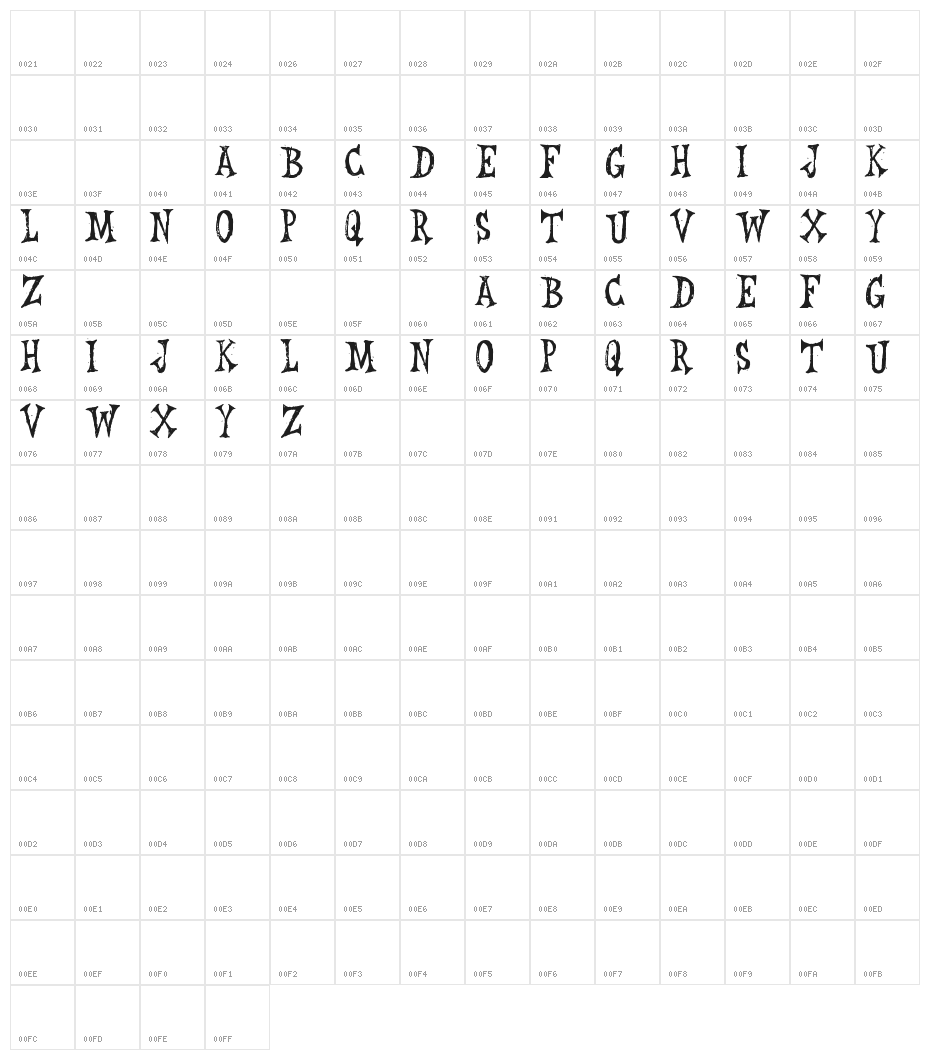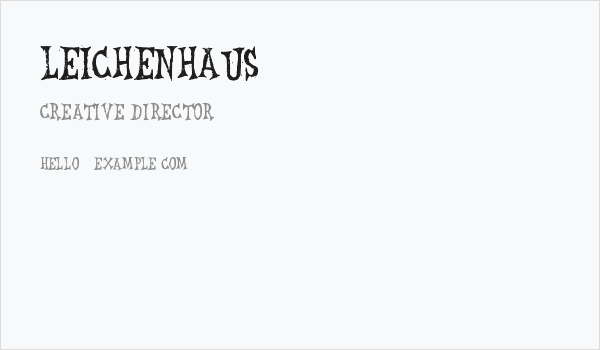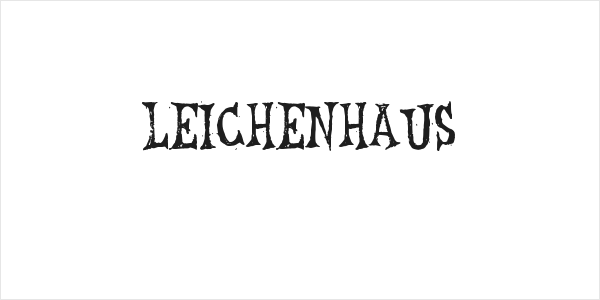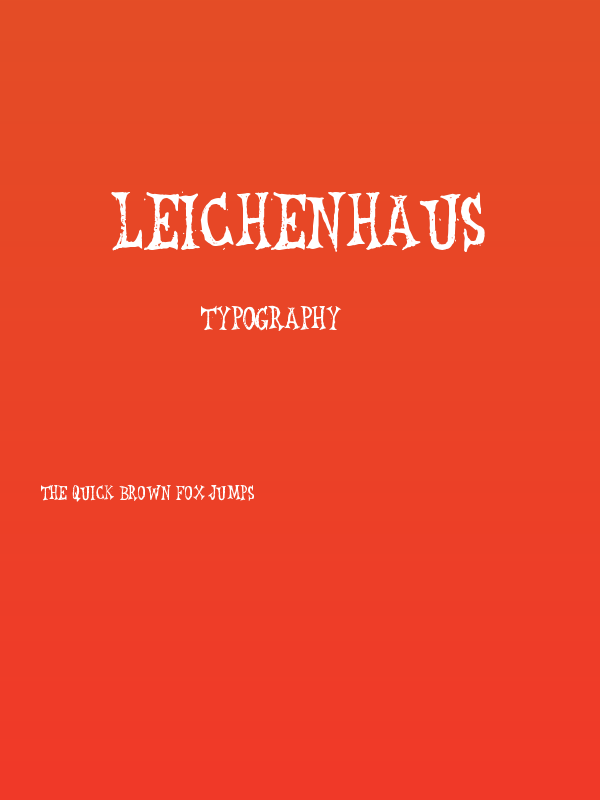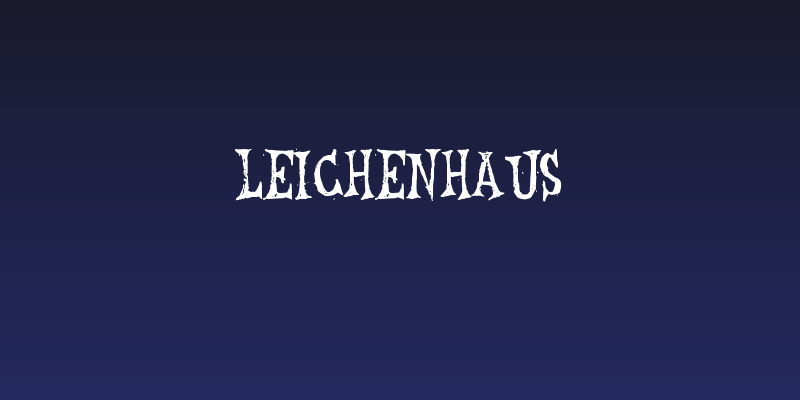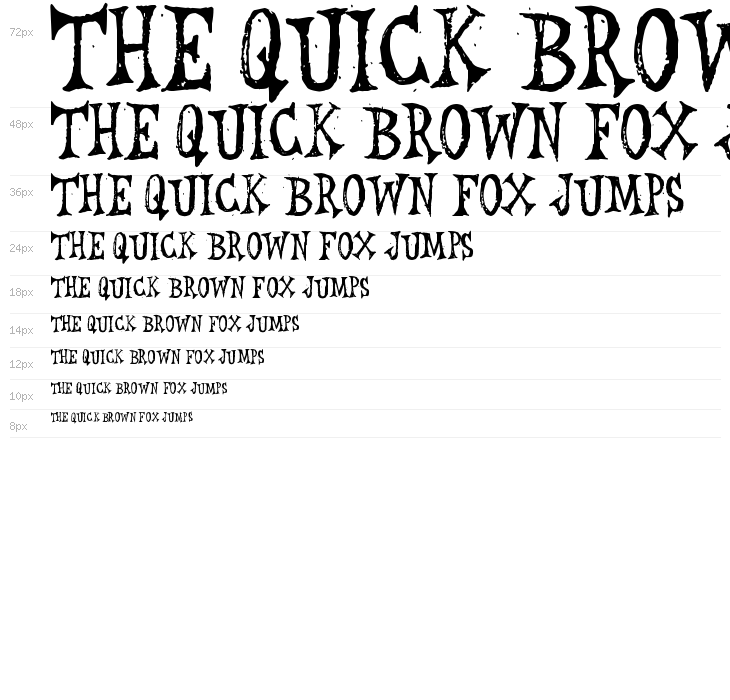
Leichenhaus Font
| Stile generale | Gothic, Decorative |
| Caso d'uso | Headlines, Posters, Logos |
| Progetti proposti | Ideal for horror-themed posters, Halloween invitations, album covers, and any project requiring a gothic or vintage aesthetic. |